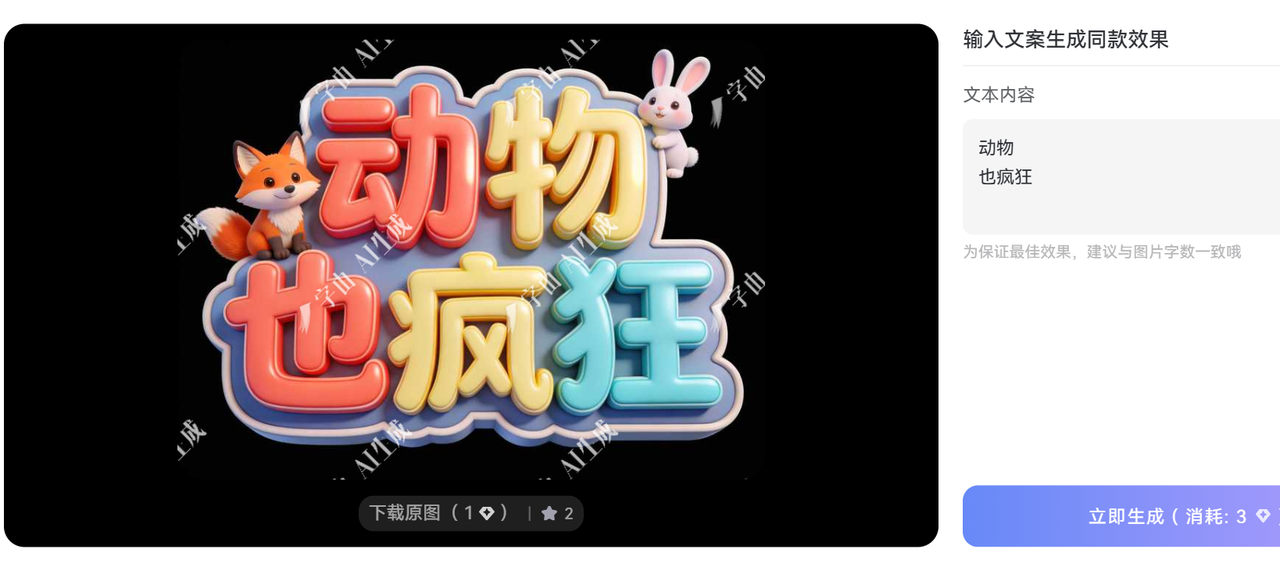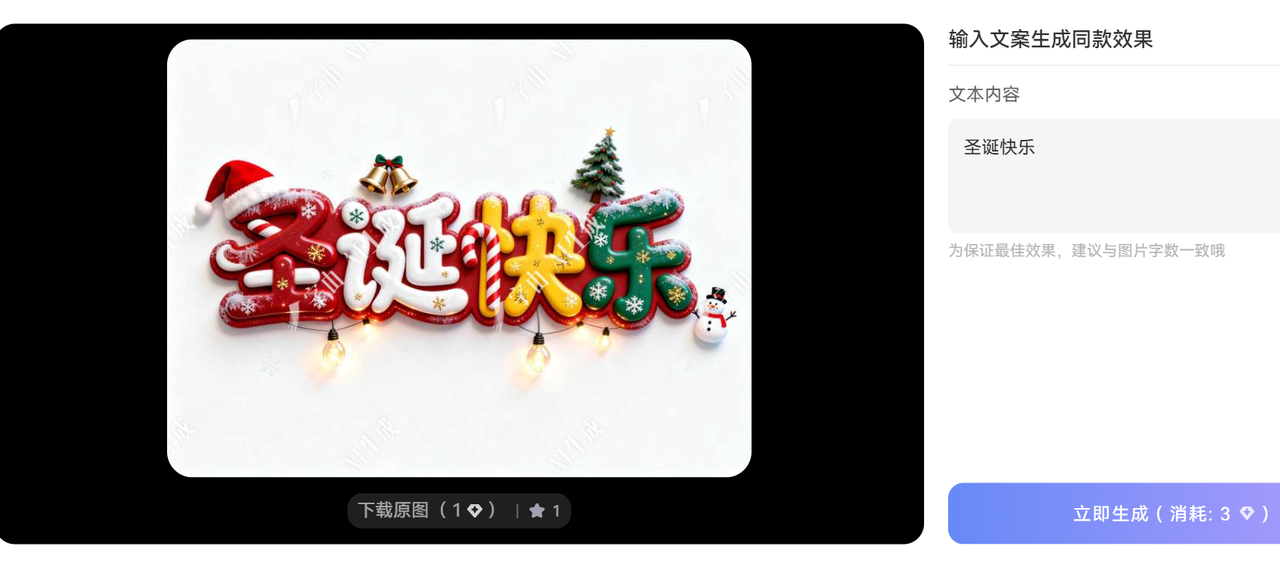
怎么获取免费商用的立体字体,教你3分钟生成和下载
做设计这几年,我最头疼的就是找立体字体。客户要求海报有视觉冲击力,想用那种有厚度、有层次感的立体字,我试过自己在PS里做立体效果,但调整参数特别耗时间,改一次甲方意见就要重新做一遍。
本文给大家推荐一个直接用工具,生成免费可商用的立体字体的方法。现在我做海报、做包装设计的效率至少提升了一半,再也不用担心版权问题,也不用花好几个小时调图层样式了。
字由AI字体生成
字由团队推出的AI字体设计工具,打开网页,选择立体字体的模板,输入你要的文字,点击一键生成,就可以快速完成立体字体的生成。我第一次用的时候是给一个咖啡品牌做包装,需要"手冲咖啡"四个大字做主视觉。直接选择一个四个字的立体模板,几分钟就生成出来了。
AI 生成立体字体的方法
打开AI字体功能页面,在搜索框中搜索“立体”,筛选出所有立体字体相关的模板
选择一个你自己喜欢的模板,并且输入自己的文字,点击一键生成即可。
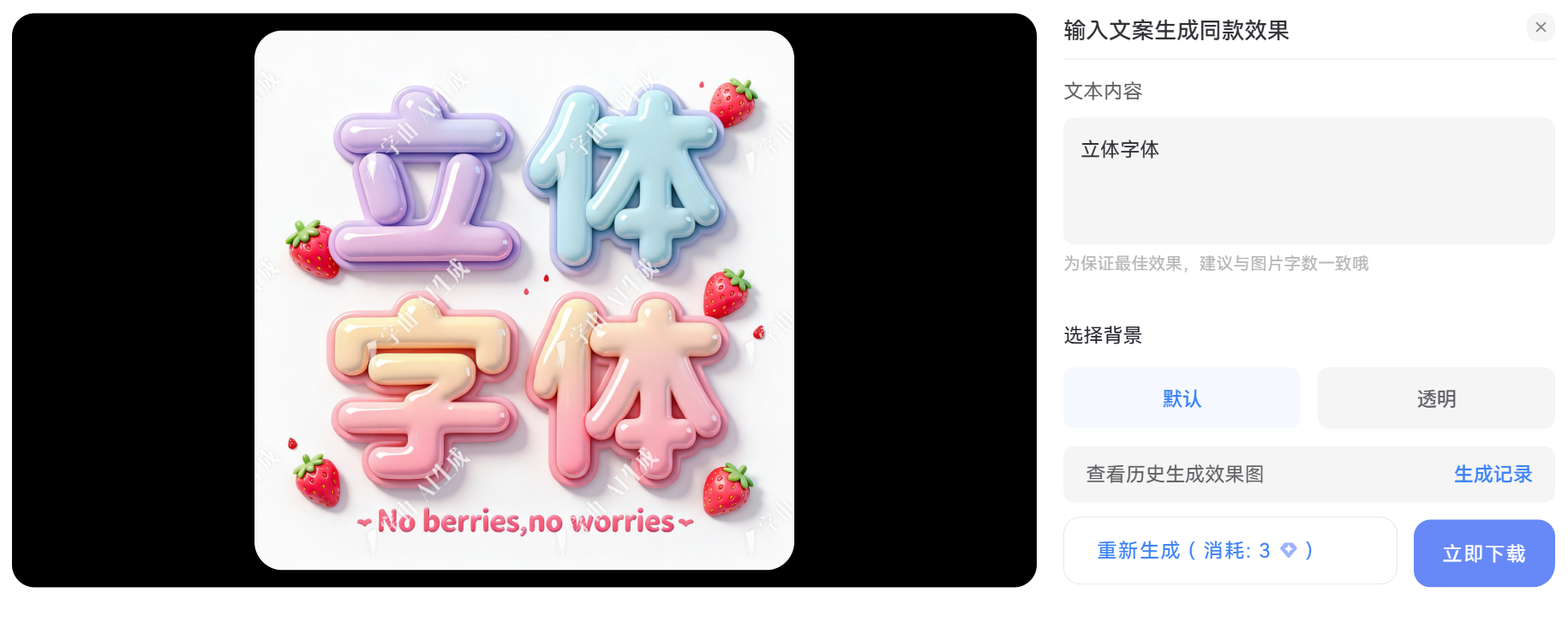
推荐几款我常用的立体字体模板
- 动物也疯狂
非常可爱的一款立体字,比较时候卡通、动漫等场景
- 圣诞快乐
一款非常明显的节日主题的模板,适合圣诞节营销使用
- 告别情书
非常适合恋综,看过的都懂
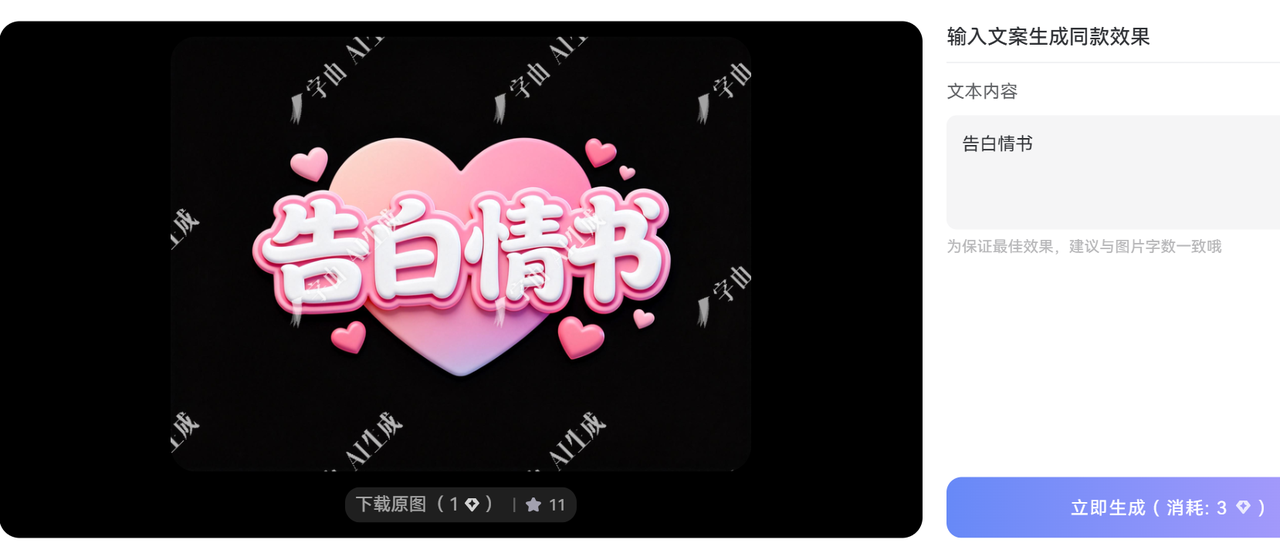
字体AI生成立体字体的优势
模板丰富
多个立体模板可以选择,其它风格的字体模板页非常丰富,基本能满足日常的设计场景
什么场景,可以试试AI生成立体字体
- 电商主图和海报
需要快速出图,字体要有冲击力,能抓住用户注意力。立体字效果可以让标题更突出,提升点击率。
- 品牌包装设计
包装上的品牌名称或者主标题,用立体字会显得更有质感和档次。我做过好几个食品包装,客户都很满意。
- 活动宣传物料
音乐节、市集、展览这类活动的海报和展架,用立体字可以营造氛围感,让人一眼就记住。
- 社交媒体内容
做公众号头图、小红书封面、抖音视频封面的时候,立体字能让画面更有层次,在信息流里更容易被注意到。
现在回想起来,我以前花那么多时间在PS里调图层样式,真的是效率太低了。